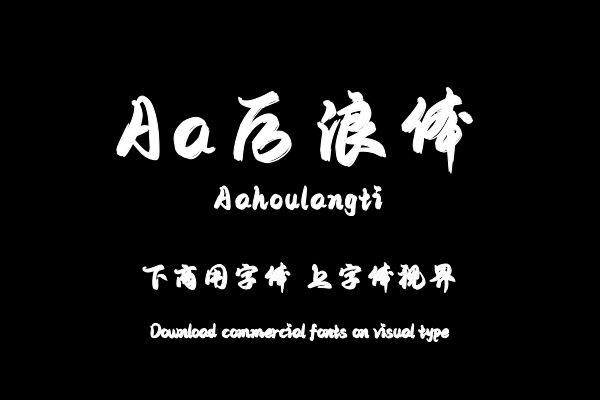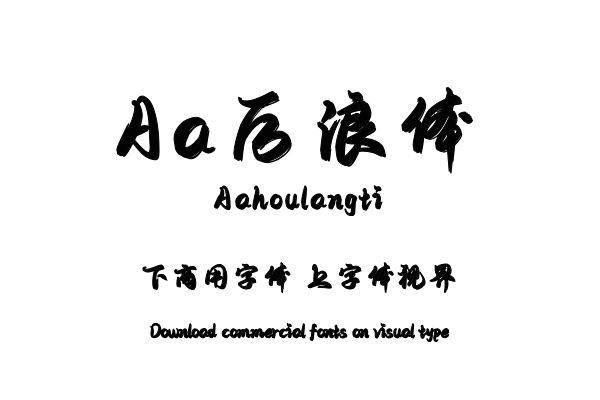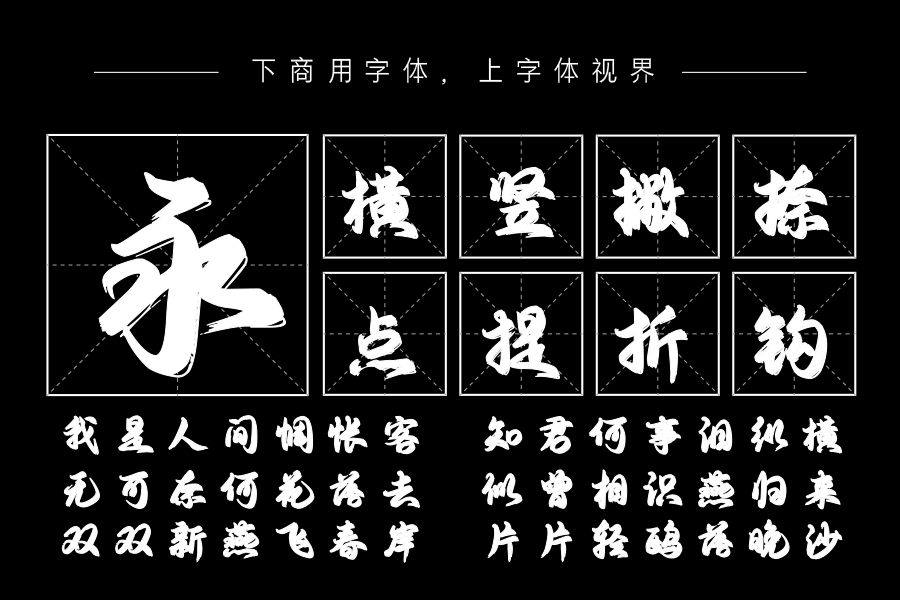
以行书技法结合手绘板的应用设计一款创意标题字体。以数位板飞白笔触结合行书写法,表现流转不断、如风似水的动感。购买须知:“下载服务费”与“字体VIP”所获得字体 仅用于个人非商用, 商用请联系付费授权。本字体为电脑用字,手机没有root权限不支持直接手机换字(手机如何root,请自行百度搜索教程)。购买前请先 了解清楚后再付款 ,字体为虚拟产品无法回收 一旦购买不支持退款。